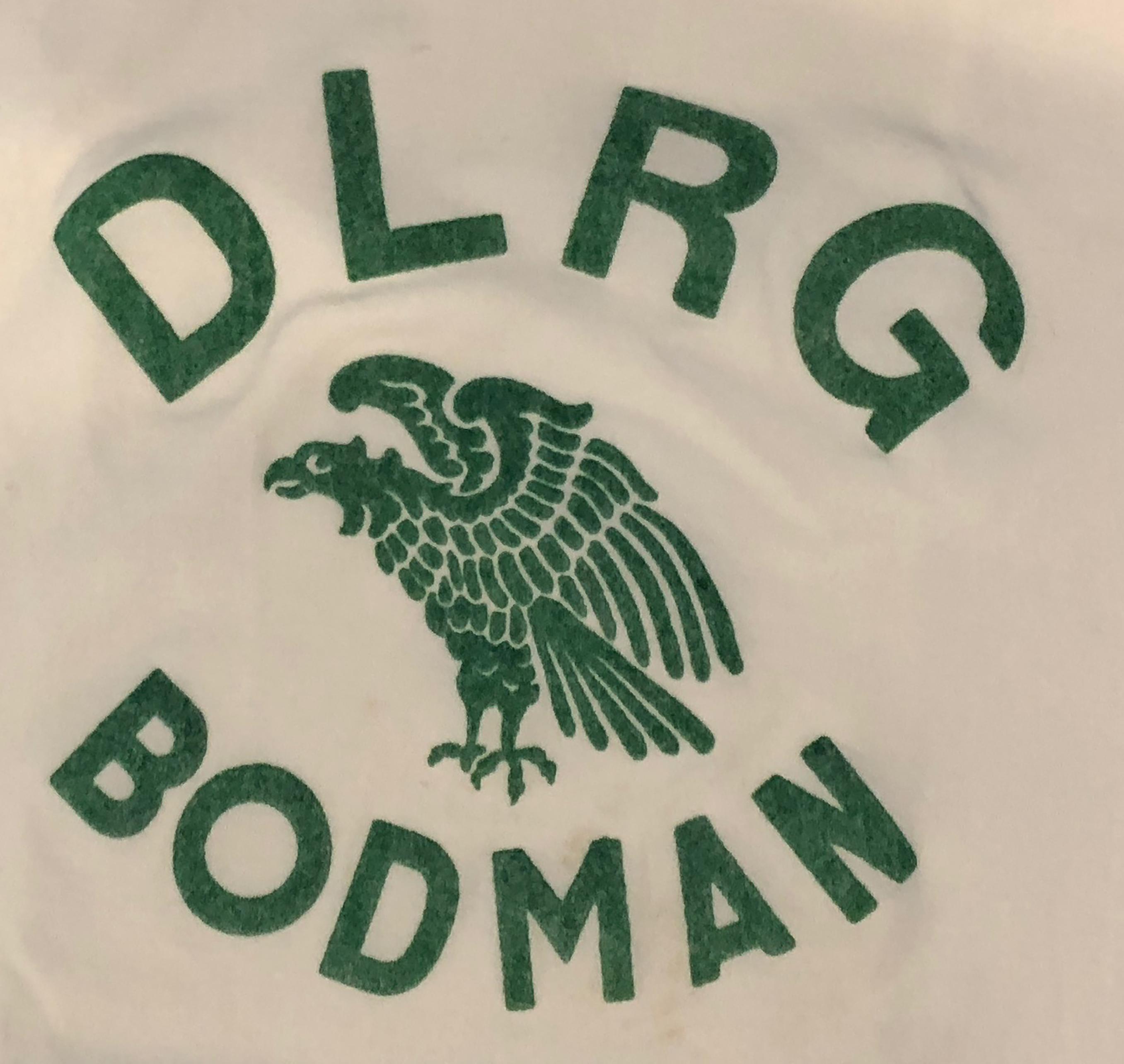
Suche Schriftart für einen Verein für die Reporoduktion von Hoodies
Uns liegt eine recht alte Beflockung eines Schirts vor, welches wir für den Verein wiederherstellen müssen. Wie so oft liegt dem Verein keine Originaldatei oder die Info zur damals verwendeten Schriftart vor.
Nach stundenlanger Suche wurden wir leider nicht wirklich fündig und hoffen daher auf Euch.
Bei der Schrift handelt sich sich um den Schriftzug "DLRG" sowie die Ortsbezeichnung "BODMAN". Vermutlich sind beide Worte aus der selben Font abzuleiten. Markant sind sicherlich das "A", "M" und das "O" aus dem Schriftzug "BODMAN".
Die Grafik ist sehr klein und unkonturiert, was eine Erkennung über Generatoren unmöglich macht.
Habt Ihr da Ideen, welche Schriftart das sein könnte? Markant sind die Großbuchstaben was die Auswahl einer alternativen Schriftart schwierig macht.